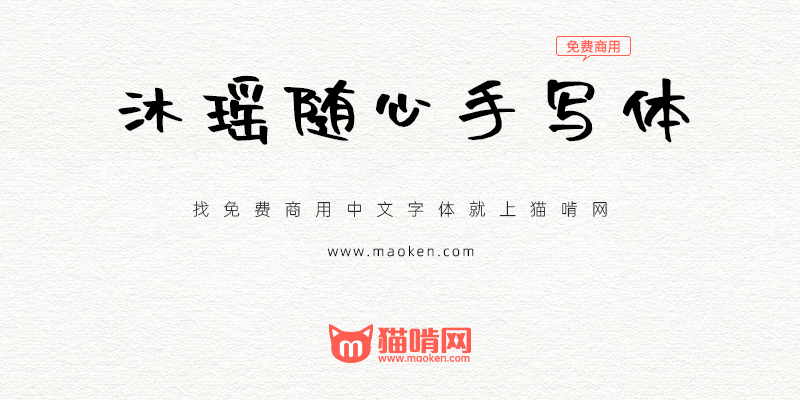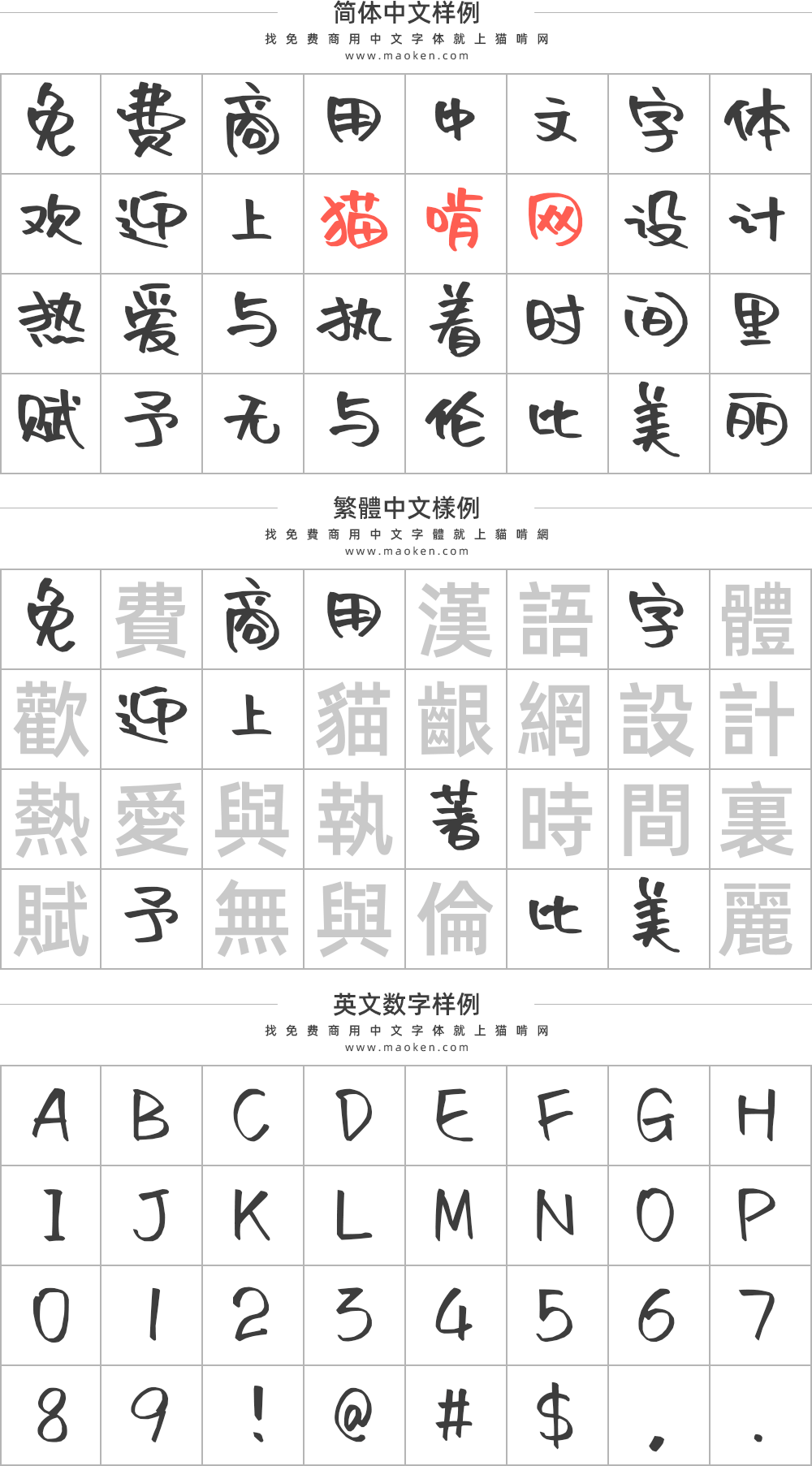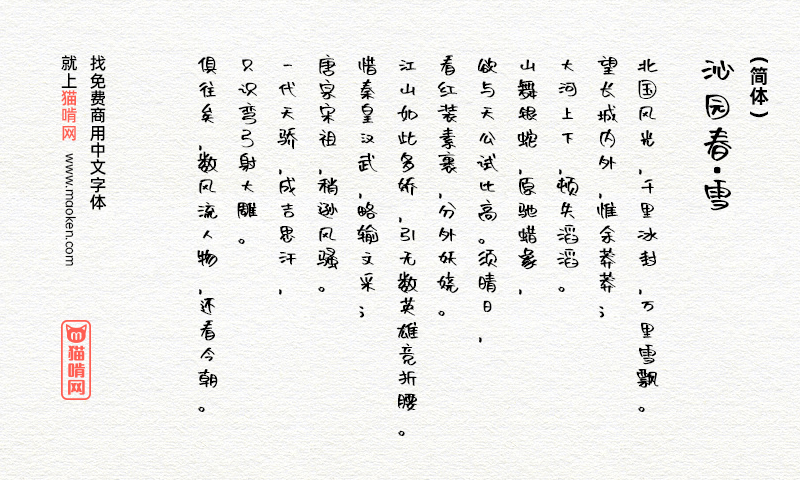
沐瑶随心手写体:随心是源于自由的快乐 免费商用手写字体
近日,是我和老婆的结婚四周年纪念日。
在这四年中,除了拥有在平凡的日子中流淌的幸福,我们也喜欢做一些创作。自从女儿(对,就是沐瑶同学,字体再次以她命名)出生之后,尽管得到了家人的帮助,创作时间依然变得碎片化,不过这无法阻止我们从生活的缝隙中攫取创作的快乐。
我和老婆的相识是起源于写字,所以我们创作了“沐瑶随心手写体”这一款字体来纪念这一时刻(为了保证手写体的一致性,这次主要是老婆完成本次创作)。这不是一款严肃的字体,而是随心的书写。
毫无疑问,困难可以分担,而快乐是可以分享的,所以当你使用字体时,若能够感受到快乐的温度,对于创作者我们而言,就是一种鼓励。
2018年7月,我发布了免费用于商用的“沐瑶软笔手写体”,每次看到它被用于各种场合,感觉很开心。时隔近一年的这一款“沐瑶随心手写体”,也希望大家能在工作学习中愉快地分享使用。在字体版权意识逐步树立的环境中,设计师在设计成本和设计效果中是左右为难的,可以说日常工作中,除了图库之外,最让人头大的就是字体版权,尤其是中文字体版权。所以,我觉得能力所能地创作让更多人使用的免费字体,也是一件有成就感的事情。
字体本身是基于GB-231280标准,共包含6763个汉字和数百个符号。